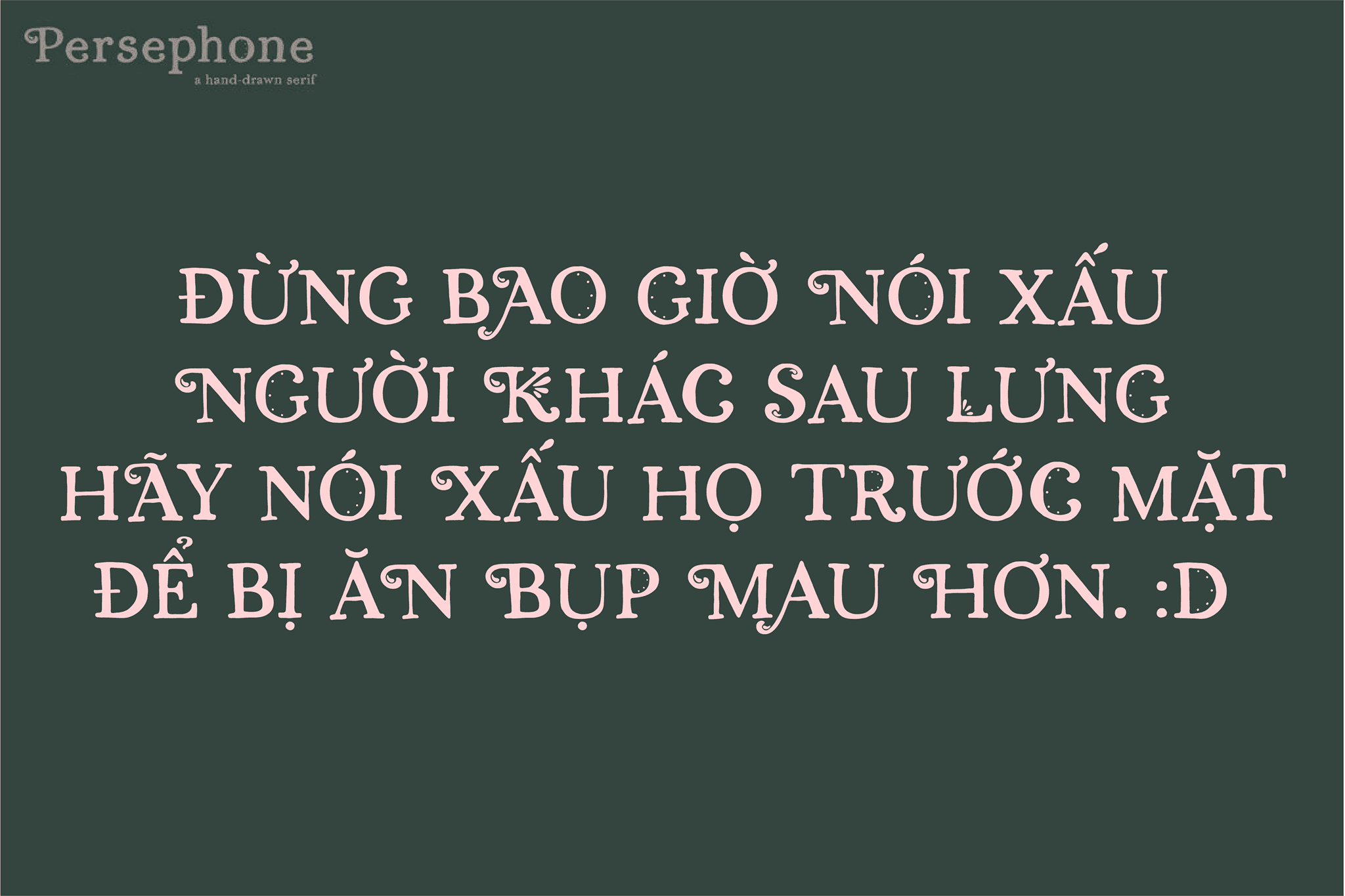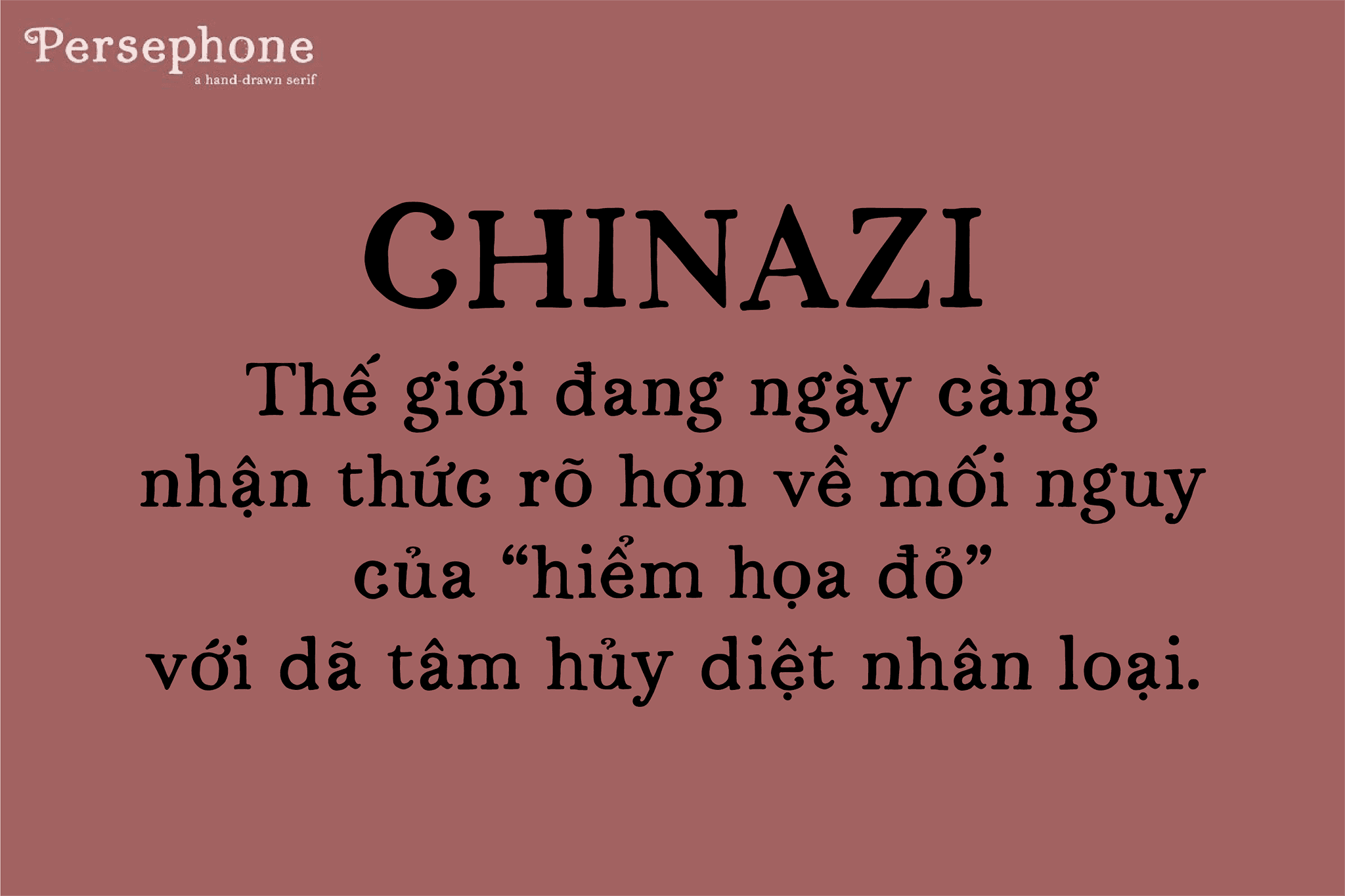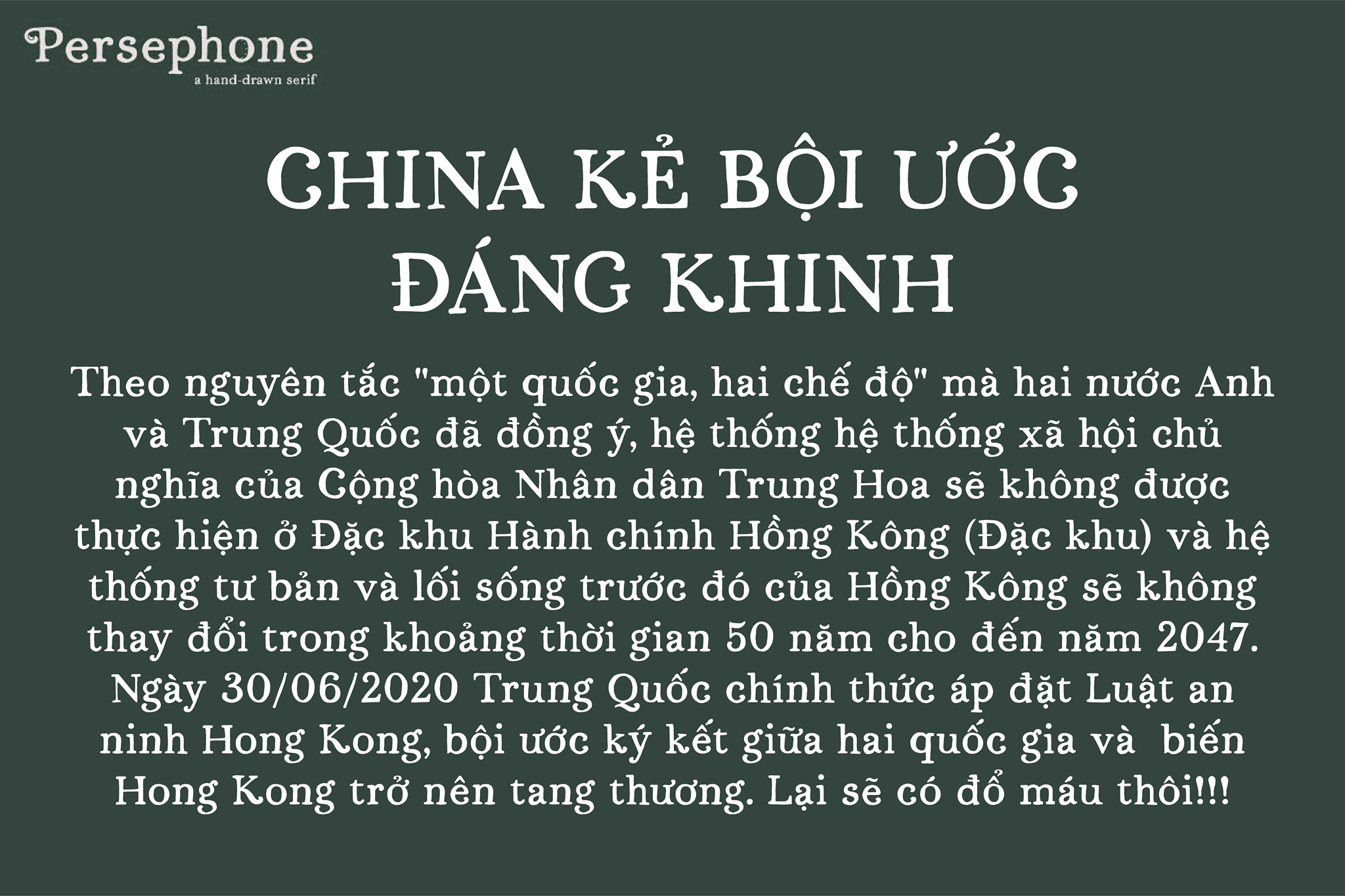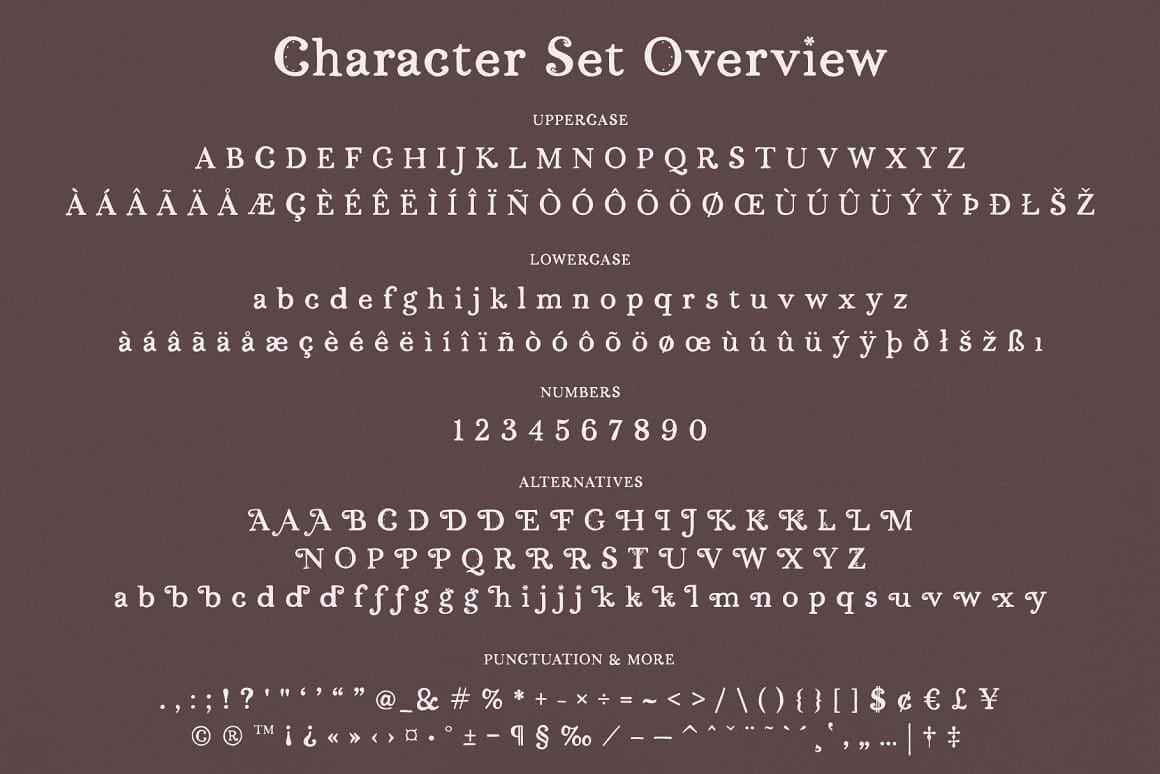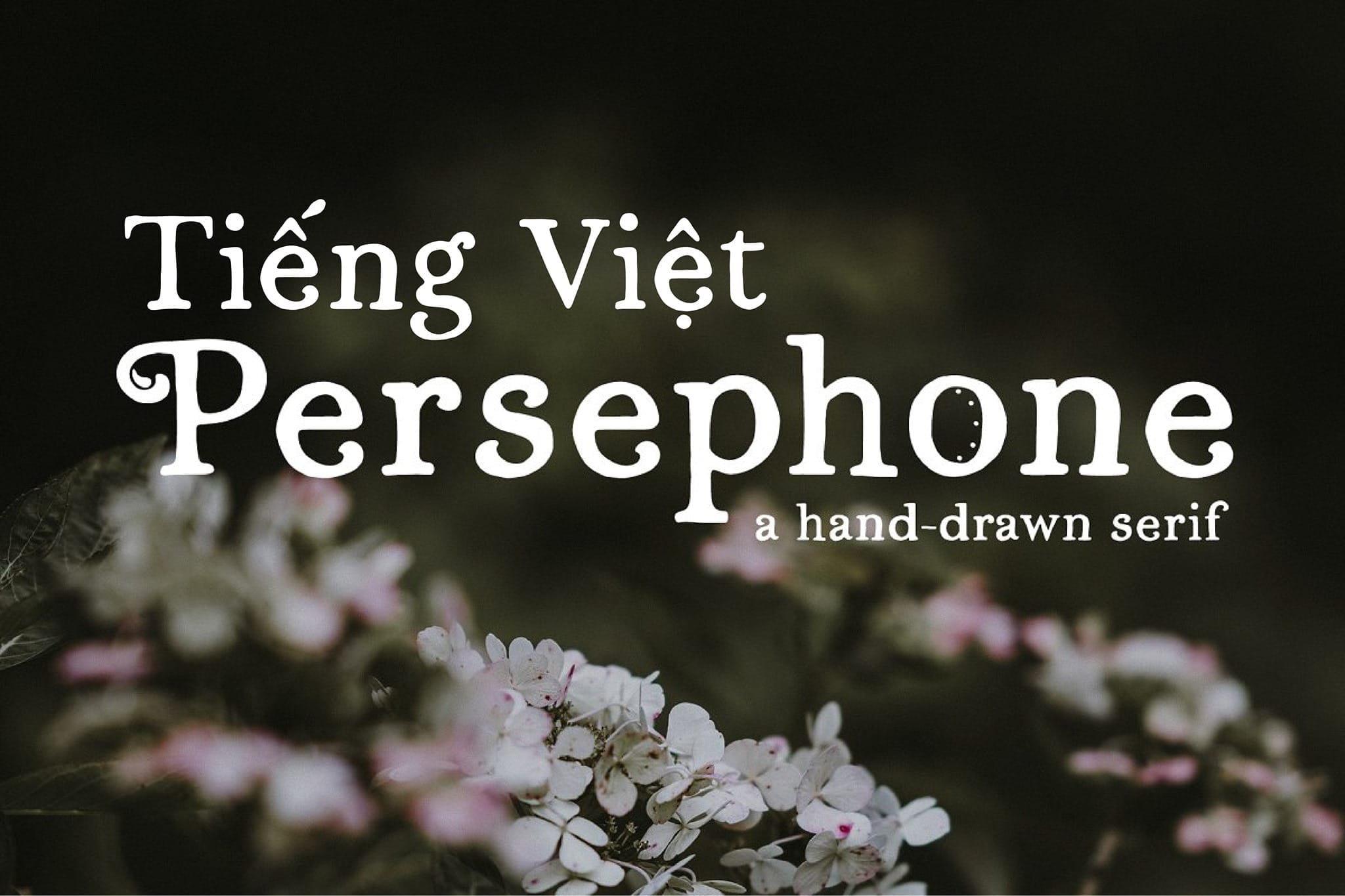
Chia sẻ font Persephone Việt Hóa
Giới thiệu font Persephone
Persephone là một phông chữ serif vẽ tay lấy cảm hứng từ mùa xuân. Phông chữ này là hoàn hảo để sử dụng cho một loạt các dự án như thiết kế logo, thương hiệu, lời mời đám cưới, bài đăng trên phương tiện truyền thông xã hội, và nhiều hơn nữa!
Các ký tự thay thế là một tính năng OpenType, do đó bạn muốn đảm bảo rằng ít nhất bạn cài đặt tệp OTF (Phông chữ OpenType). Khi phông chữ được cài đặt, bạn có thể truy cập các chữ cái đó bằng cách mở bảng / menu glyphs trong bất kỳ ứng dụng hoặc chương trình nào bạn đang sử dụng.